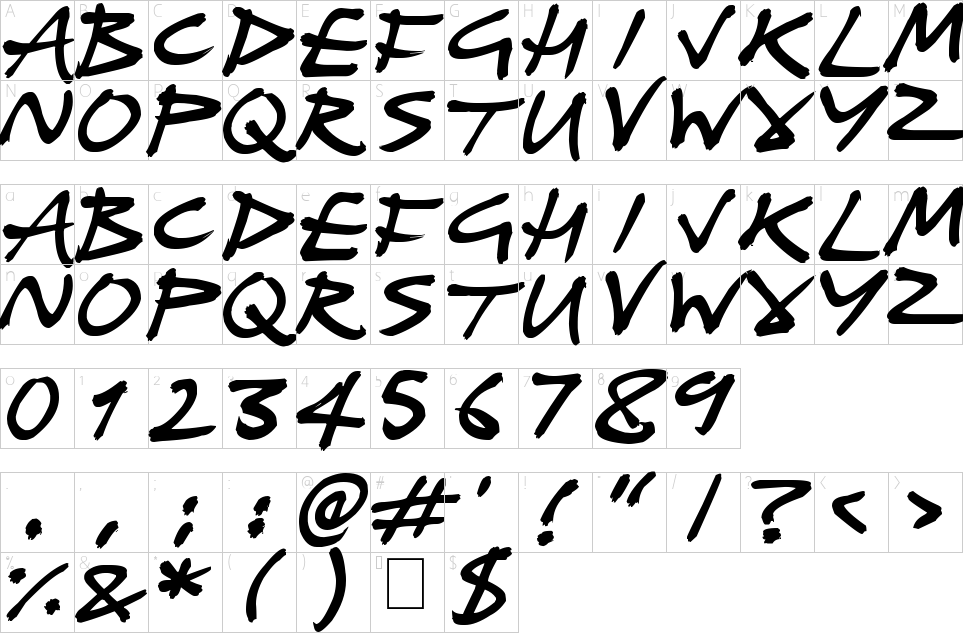
A fonte Pirate Plunder é uma opção gratuita e divertida para quem procura um desenho peculiar para seus projetos digitais. Desenvolvida pelo designer Darrell Flood, esta fonte ganhou muitos downloads, totalizando 2.961. Pirate Plunder combina elementos de piratas e mar com uma forma arredondada e um pouco irregular, criando um estilo único e vibrante. Perfeita para adicionar um toque especial a qualquer projeto, seja para criar logotipos, adicionar texturas a imagens ou mesmo para dar um toque de personalidade a mensagens de e-mail. Se você está procurando por algo diferente e com um ar pirata, Pirate Plunder é uma ótima escolha.